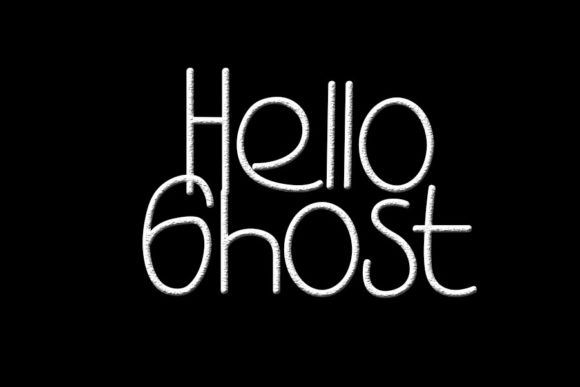
Название: Hello Ghost Font
Hello Ghost - простой, симпатичный и круглый рукописный шрифт.
Независимо от темы, этот шрифт станет отличным дополнением к вашей библиотеке шрифтов, поскольку он способен возвысить любое творение.